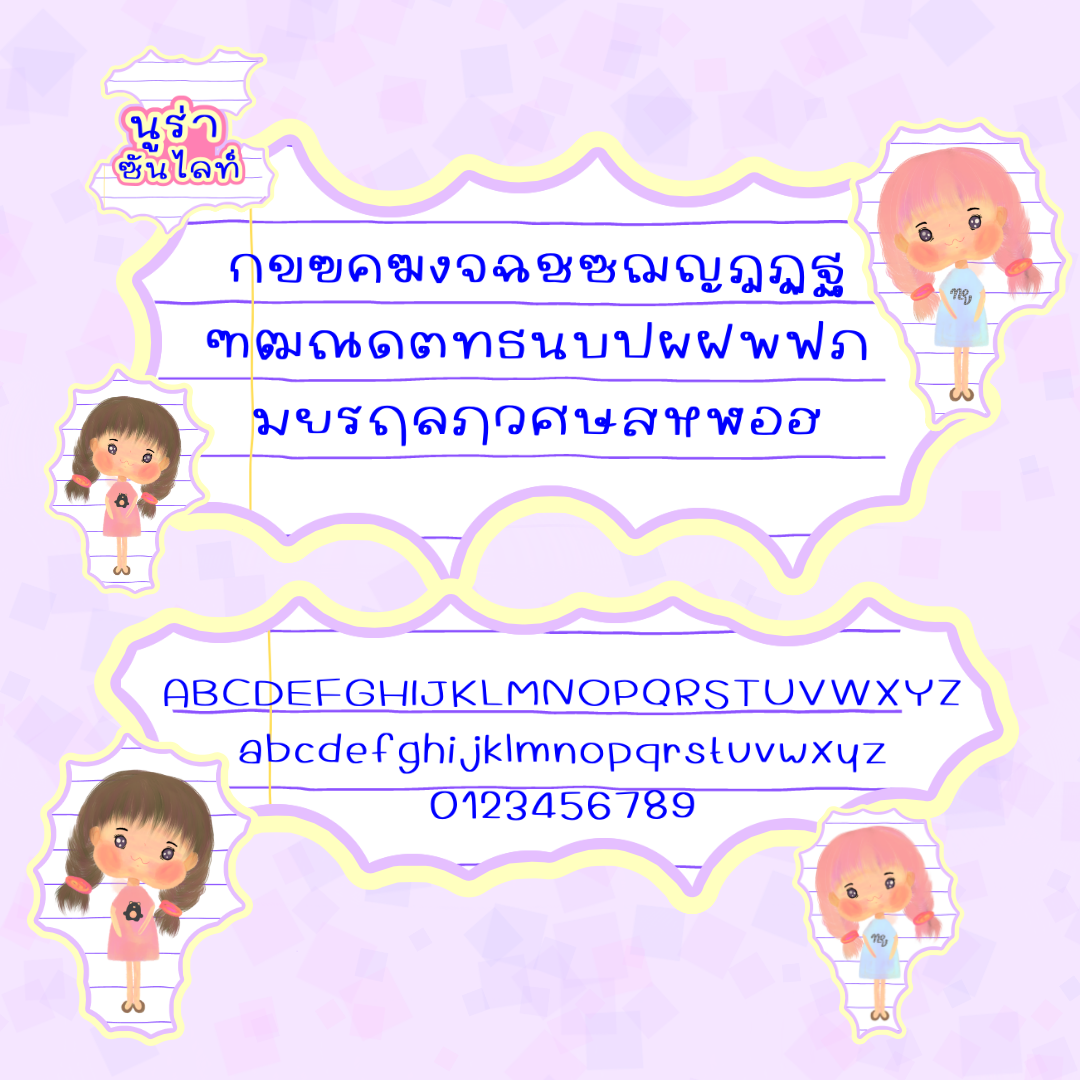
นูร่าซันไลท์ (Nura sunlight)
ฟอนต์ลายมือตัวบาง อวบๆ มีความเป็นมาร์กเกอร์น้อยๆ ฟอนต์มีด้วยกัน 3 น้ำหนัก คือ บาง ปกติ หนา  นูร่าราดาเปิดให้ใช้ฟรีส่วนตัว น้ำหนักบางนะคะ